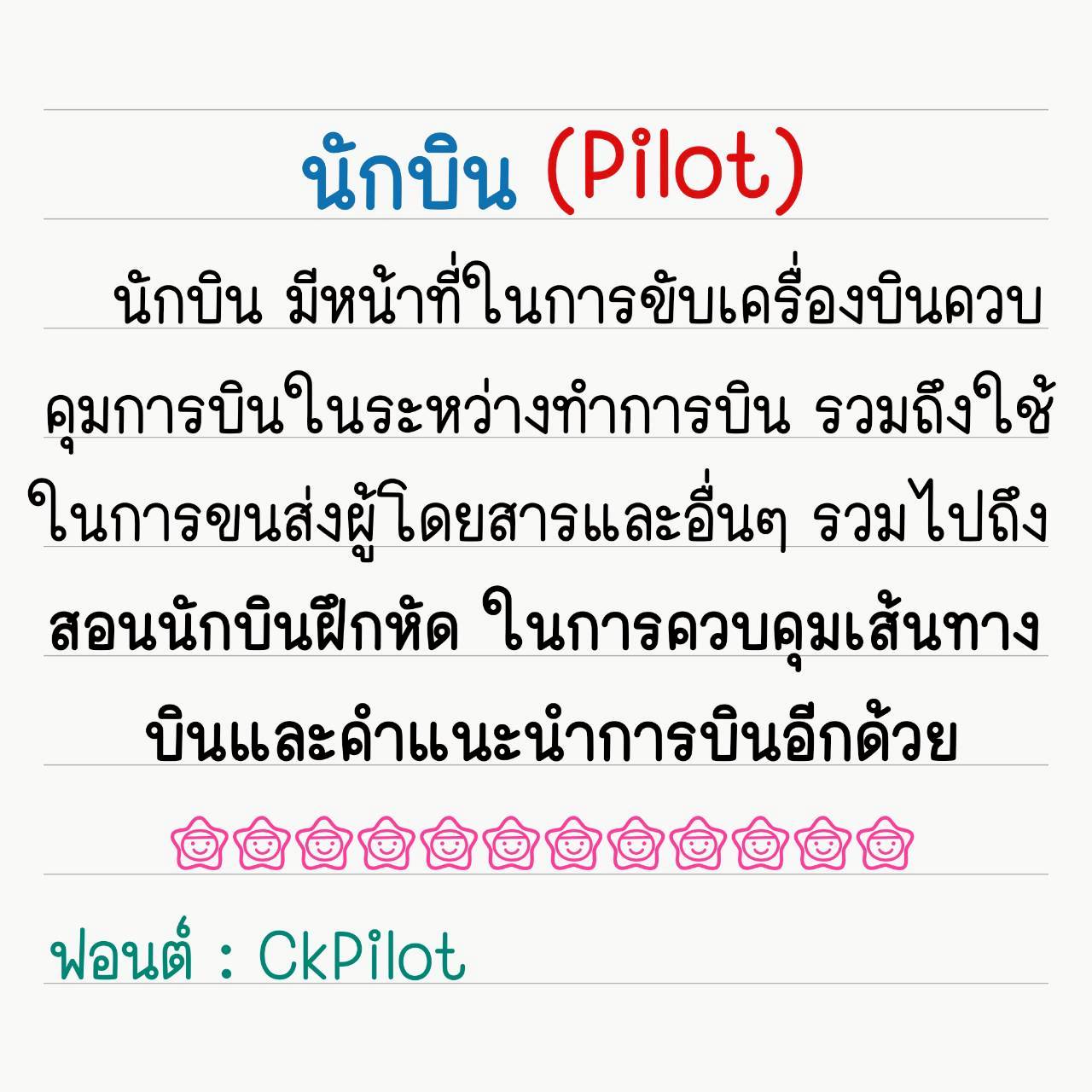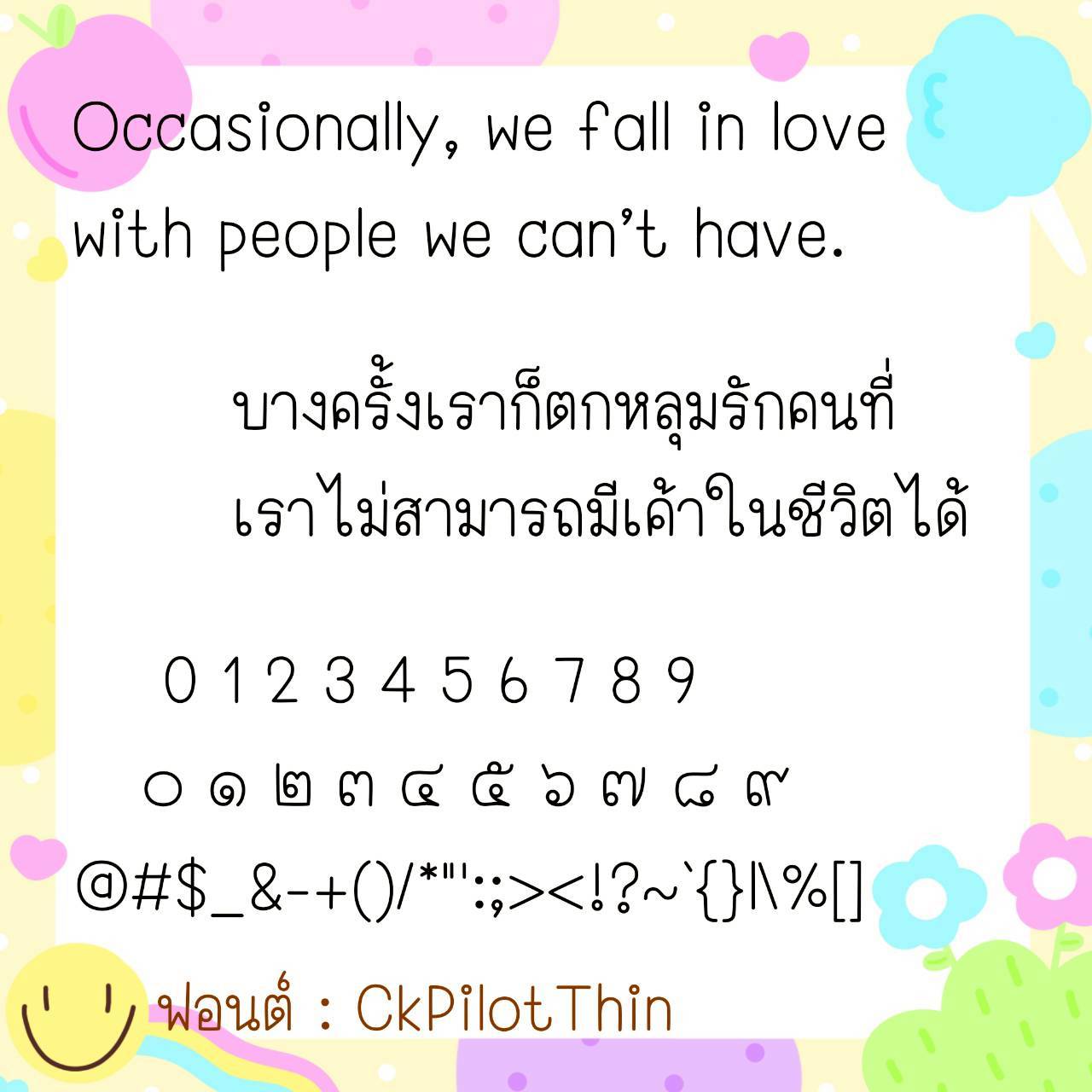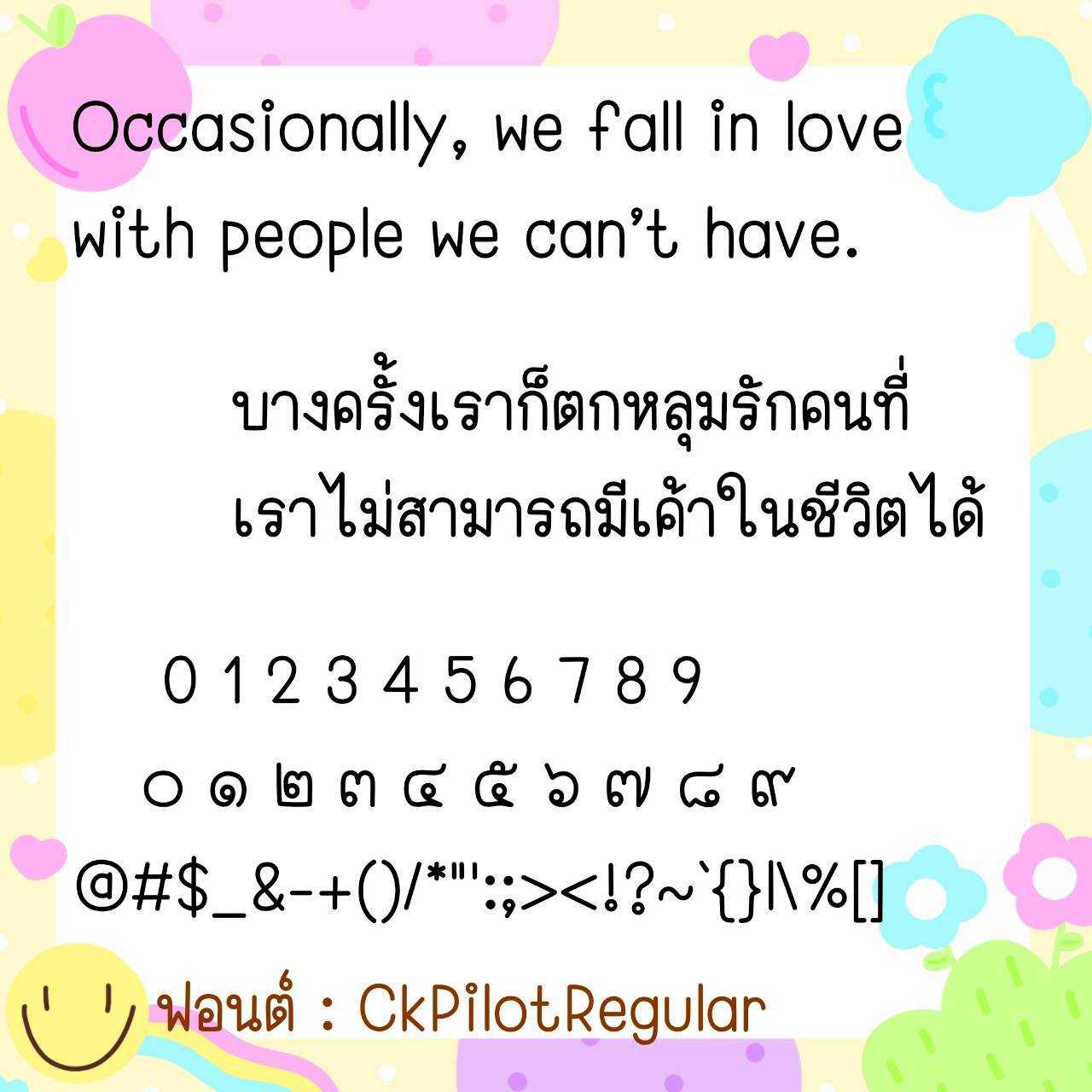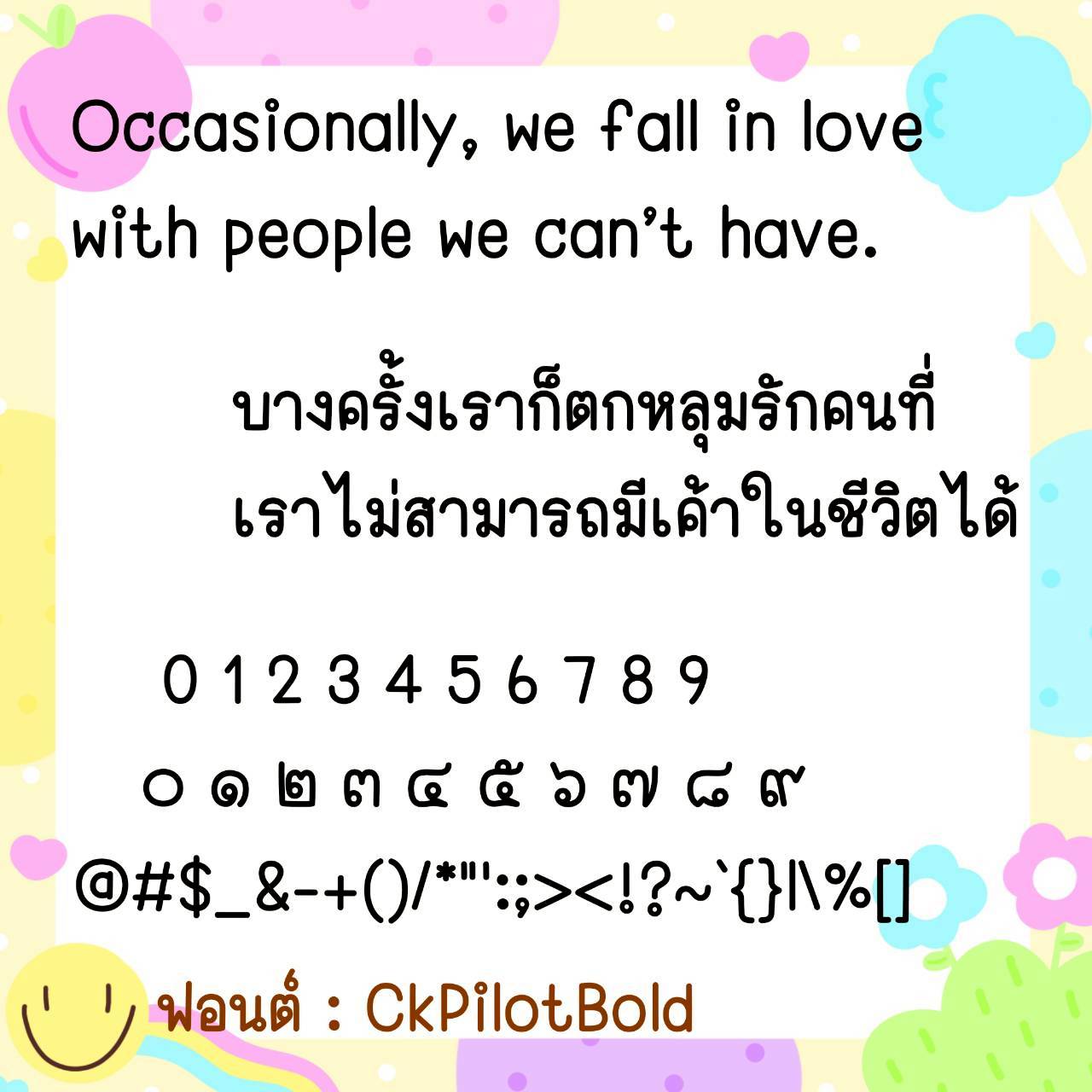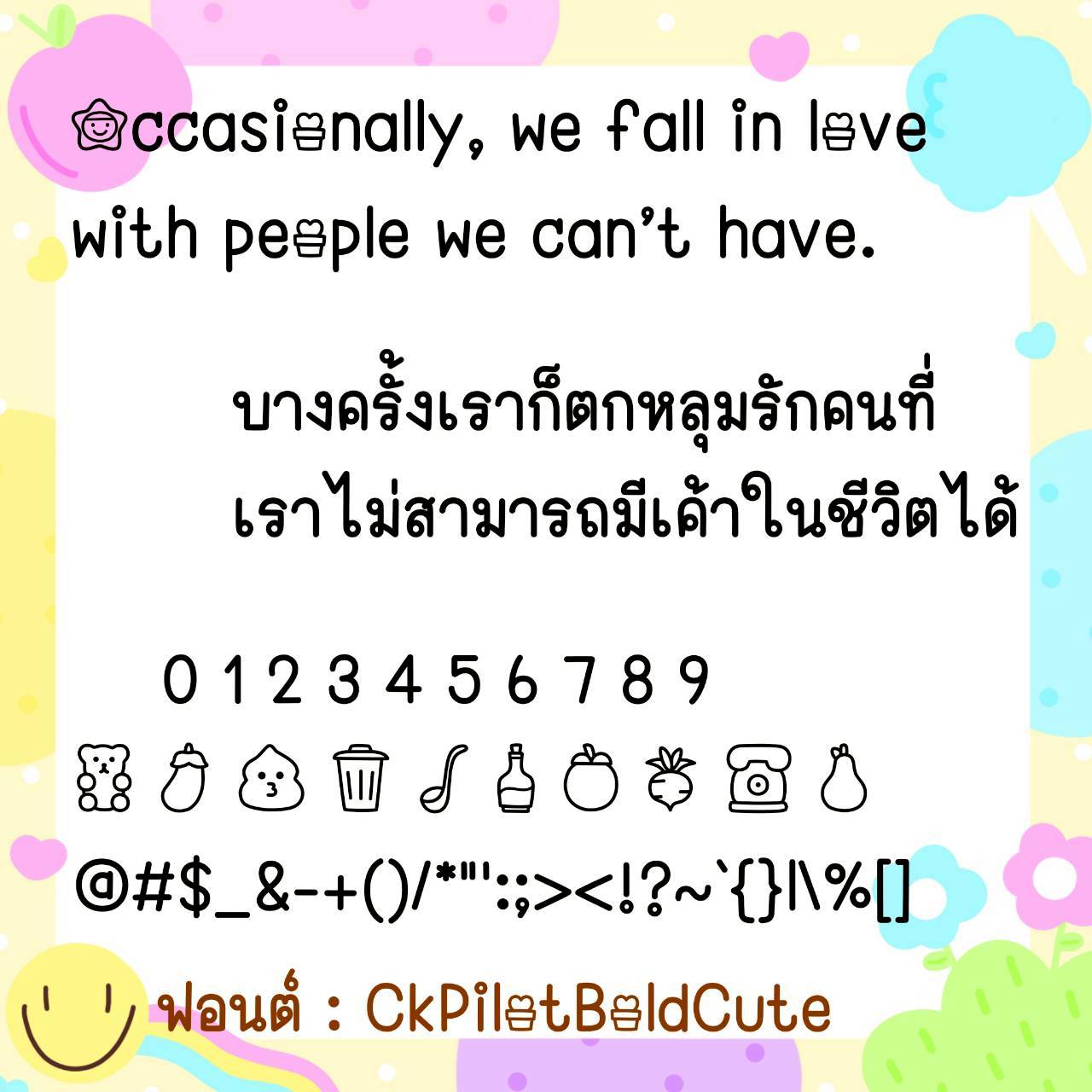
Font CkPilot
ชื่อสินค้า : Font CkPilot 💙
🔸 ฟอนต์ลายมือแนวเป็นระเบียบเรียบร้อยมากๆ ขนาดฟอนต์กำลังพอดีไม่อ้วนไม่ผอมจนเกินไป เน้นอ่านง่ายสบายตาสุดๆ และยังมีไฟล์อิโมจิน่ารักๆ ที่ใช้แทนเลขไทยให้ด้วยค่ะ 🥰💙
🔹 The handwriting font is very neat and tidy. The font size is just right, not too fat or too thin. It emphasizes easy reading and is very pleasing to the eyes. There is also a file of cute emojis that can be used instead of Thai numbers. 🥰💙